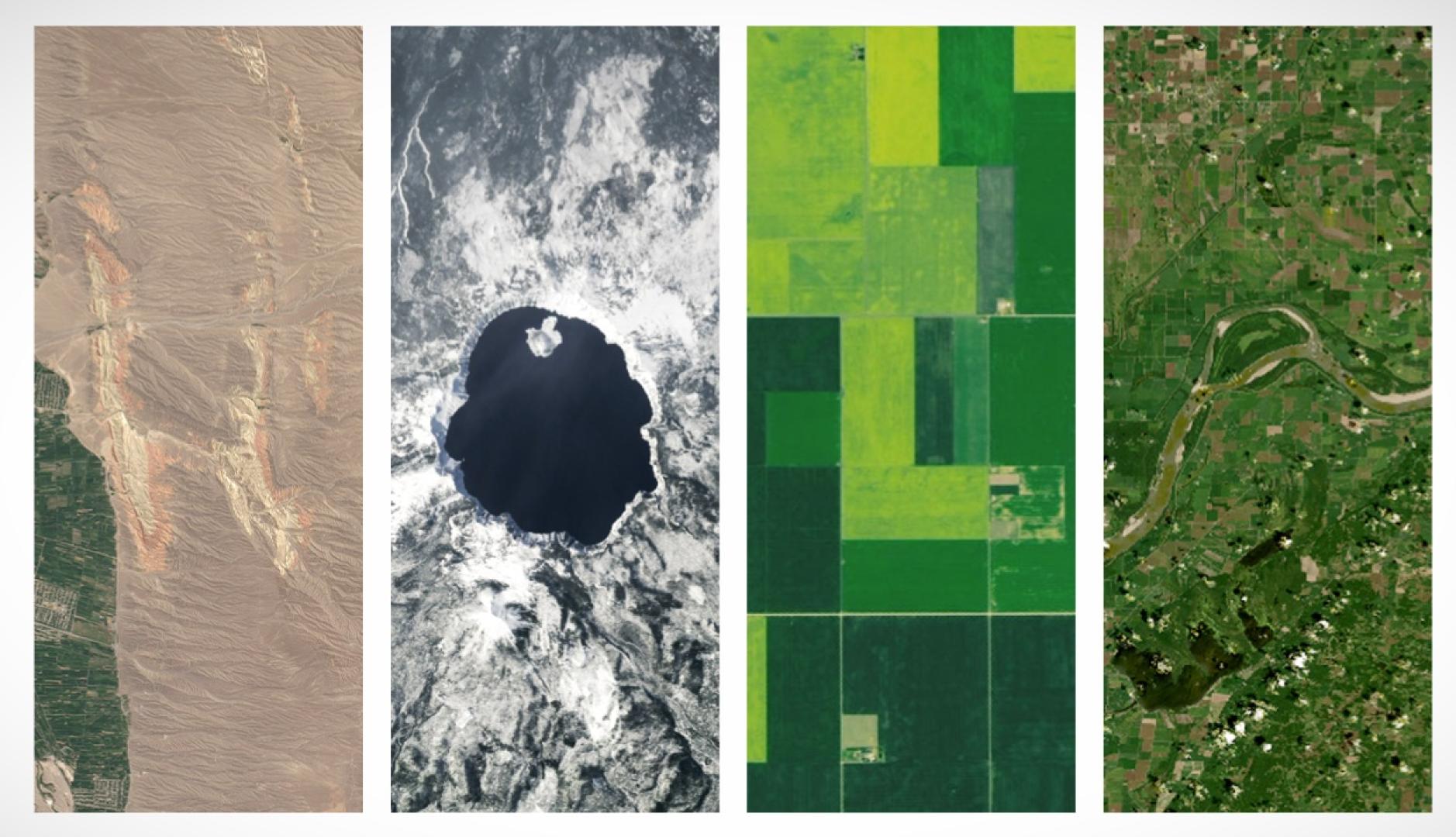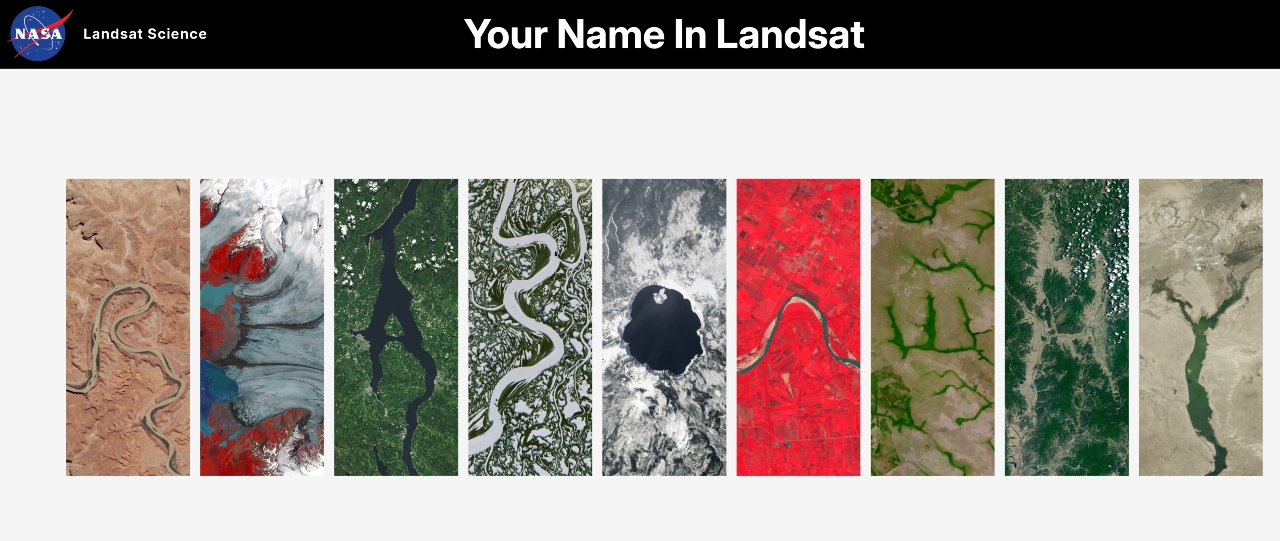
La NASA convierte la Tierra en tipografía con imágenes satelitales en una herramienta interactiva
• El generador “Your Name in Landsat” permite escribir palabras con paisajes reales del planeta
• La iniciativa busca poner en valor el papel de la observación satelital en la comprensión del planeta
Hola escrito con la herramienta, cada letra es una imagen satelital
La NASA ha desarrollado una herramienta digital que transforma imágenes satelitales de la Tierra en un sistema tipográfico. Bajo el nombre “Your Name in Landsat”, el generador permite a los usuarios escribir cualquier palabra utilizando fotografías reales de ríos, lagos, campos o formaciones naturales captadas desde el espacio. La iniciativa, compartida por el Kennedy Space Center con motivo del Día de la Tierra, propone una forma visual y accesible de explorar el planeta a través del diseño.
Al introducir un texto, la herramienta construye cada letra a partir de una base de datos de imágenes
Aunque su difusión actual responde a esta efeméride, la herramienta no es nueva. La NASA la presentó por primera vez en agosto de 2024 en el marco de Camp Landsat, un campamento virtual de verano impulsado por la agencia. Desde entonces, se ha construido sobre el archivo del programa Landsat, la misión de observación terrestre más longeva, iniciada en 1972 y con más de 50 años de registros, para ofrecer una experiencia interactiva que convierte datos científicos en lenguaje visual.
Al introducir un texto, la herramienta construye cada letra a partir de una base de datos de imágenes. Y al interactuar con cada carácter, el usuario puede conocer la ubicación exacta del paisaje, así como sus coordenadas, convirtiendo la experiencia en una combinación de exploración visual y aprendizaje geográfico. Sin embargo, no todas las letras cuentan con la misma representación. Algunas disponen de múltiples variantes en función de la abundancia de formas similares en la naturaleza. Es el caso de la “A”, que ofrece hasta cinco opciones distintas, con paisajes que van desde el delta del Yukón, en Alaska, hasta el lago Guakhmaz, en Azerbaiyán. Otras letras, en cambio, son más escasas. La “G”, por ejemplo, solo cuenta actualmente con una única representación en la galería: una imagen captada en Fonte Boa, en el estado de Amazonas, en Brasil.
Reason.Why escrito con la herramienta “Your Name in Landsat”
El proyecto busca poner en valor el papel de la observación satelital en la comprensión del planeta. Y es que las imágenes que alimentan el generador constituyen una base crítica para la toma de decisiones en ámbitos como la gestión de recursos naturales o la planificación medioambiental. La herramienta traduce ese volumen de datos en una experiencia comprensible y compartible, acercando la ciencia a nuevos públicos.
En este sentido, la propuesta conecta con iniciativas recientes que utilizan imágenes satelitales como base para construir identidad visual y relato territorial, como el desarrollo de la marca de la Amazonía brasileña, que también ha empleado patrones naturales y coordenadas reales para generar un sistema gráfico. En ambos casos, el territorio deja de ser únicamente contexto para convertirse en materia prima creativa.
La acogida de “Your Name in Landsat” ha sido inmediata en redes sociales, donde la publicación original ha superado los 50 millones de visualizaciones en menos de una semana.
Este post ha generado miles de interacciones, incluidas las de marcas como Xbox que han utilizado la herramienta para crear sus propios mensajes.
Este alcance refuerza el potencial de la iniciativa como vehículo de divulgación, al convertir datos científicos en contenido cultural y participativo.